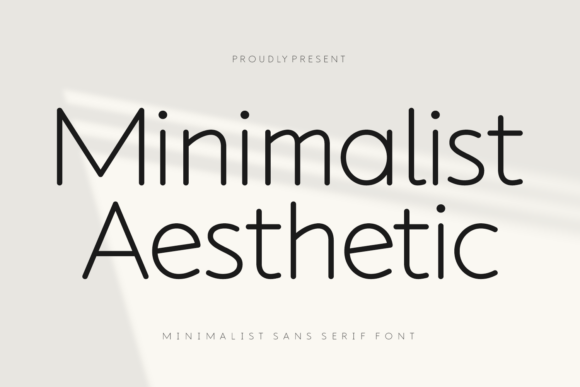
Minimalist Aesthetic
Wenn Sie nach hochwertigen Assets wie Minimalist Aesthetic suchen, ist dieses Premium-Paket eine fantastische Wahl für Ihre kreativen Projekte.
Egal, ob Sie POD-Produkte (Print on Demand), Hochzeitseinladungen oder Social-Media-Grafiken erstellen, Minimalist Aesthetic ist die ideale Wahl.